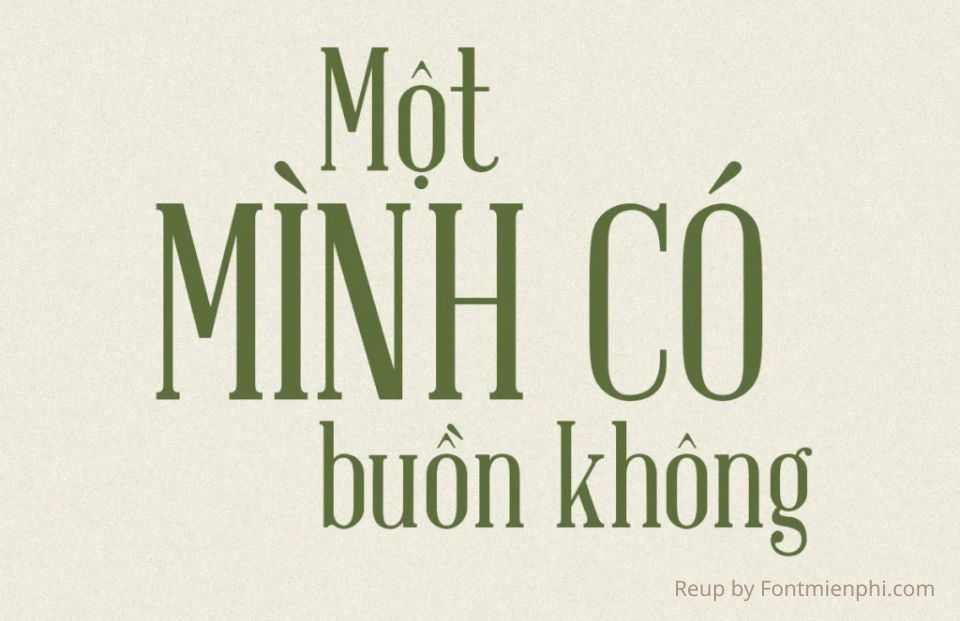
Font VL Abraham Lincoln Regular Việt Hóa Miễn Phí
Giới Thiệu: Font VL Abraham Lincoln Regular Việt Hóa Miễn Phí
Tiếp tục chuỗi chia sẻ những tài nguyên thiết kế chất lượng, hôm nay Fontmienphi.com xin giới thiệu đến bạn một font chữ mang đậm nét thời gian: Font VL Abraham Lincoln Regular.
Đây là một phông chữ có chân (Serif) tuyệt đẹp đã được Font Việt Linh dày công Việt hoá. Với việc hỗ trợ đầy đủ bộ gõ tiếng Việt cùng hệ thống dấu chuẩn xác, VL Abraham Lincoln Regular giúp bạn dễ dàng thao tác và ứng dụng ngay vào các dự án thiết kế dành riêng cho thị trường Việt Nam mà không phải lo lắng về vấn đề lỗi hiển thị.
Phông chữ này khoác lên mình một kiểu dáng cổ điển, nhuốm màu hoài niệm với những nét chân mềm mại và tỷ lệ chữ vô cùng cân đối. Nó mang lại một cảm giác vừa trang trọng, bề thế nhưng lại rất đỗi gần gũi. Chính linh hồn này đã biến VL Abraham Lincoln Regular trở thành mảnh ghép hoàn hảo cho những dự án thiết kế theo đuổi phong cách Cổ điển – Vintage – Hoài niệm.
🌟 Đặc Điểm Nổi Bật Của Font VL Abraham Lincoln Regular
• Vẻ đẹp hoài cổ: Phong cách thiết kế mang đậm dấu ấn thời gian, tạo cảm giác sang trọng và truyền thống.
• Việt hóa chuẩn mực: Hỗ trợ đầy đủ các ký tự và dấu tiếng Việt mượt mà, giúp quá trình làm việc trơn tru hơn.
• Độ ổn định cao: Trọng lượng (weight) Regular giúp font giữ được sự rõ ràng, dễ đọc, lý tưởng để sử dụng cho cả tiêu đề (headline) lẫn các đoạn nội dung ngắn cần nhấn mạnh cảm xúc.
• Khả năng kết hợp ấn tượng: Khi được “mix & match” cùng các font sans-serif (không chân) hiện đại, VL Abraham Lincoln Regular sẽ tạo ra một sự tương phản cực kỳ thú vị giữa nét cổ điển và đương đại, mang lại chiều sâu nghệ thuật cho tổng thể thiết kế.
🎨 Ứng Dụng Thực Tế
Với tinh thần hoài niệm đặc trưng, VL Abraham Lincoln Regular đang được chia sẻ miễn phí trên Fontmienphi.com sẽ tỏa sáng rực rỡ trong các ấn phẩm như:
• Thiết kế bìa sách, dàn trang tạp chí mang âm hưởng xưa cũ hoặc văn học cổ điển.
• Sáng tạo poster, banner cho các sự kiện văn hoá, lịch sử hoặc triển lãm nghệ thuật.
• Thiết kế bao bì nhãn mác cho các sản phẩm thủ công mỹ nghệ, đặc sản địa phương hoặc hàng hóa truyền thống.
• Xây dựng bộ nhận diện thương hiệu (branding) cho các doanh nghiệp, tổ chức muốn nhấn mạnh vào bề dày lịch sử, giá trị di sản và sự uy tín lâu đời.